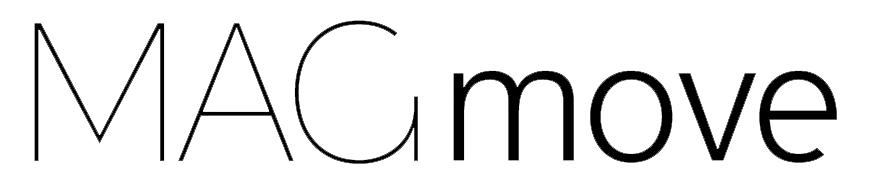
Schriftart von Mag move Logo gesucht
für den Nachbau eines Logos suche ich die Schriftart/en, auf der das Logo basiert bzw. ähnliche Schriftarten.
Der Kunde hat leider dazu keine Unterlagen mehr und möchte das Logo nachgebaut haben.
G und e sind ja sehr charakteristisch, aber ich habe nichts passendes gefunden. Habt ihr dazu eine Idee?